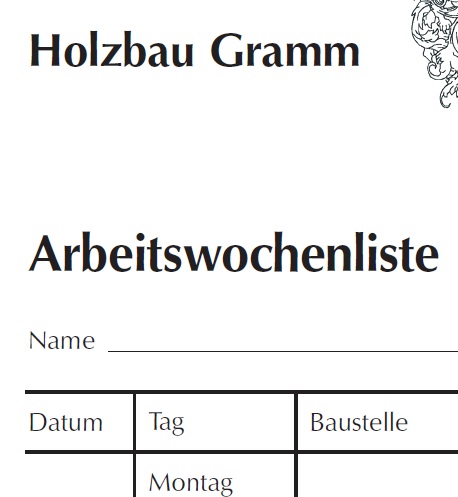
Font October SB roman und SB medium gesucht!
habe gerade einen Anruf aus meiner Hausdruckerei bekommen, dass deren Font October SB roman und SB medium 0 kb anzeigt und nicht mehr funktioniert. Ich konnte denen leider nicht aushelfen, wo man diese Schrift nachkaufen kann (oder downloaden falls freefont). Die Leute dort benutzen MAC. Weiß jemand von euch, wo man die herkriegt? Bekomme in den nächsten Minuten noch einen Screen. Angeblich soll sie recht unspektakulär wirken, ähnlich der Myriad.
Das war der Optima Clone der Firma Scangraphic.
SB bedeutet Scangraphic Bodytype (also für den Textbereich).
Es gab auch SH (Scangraphic Headline).
Diese Familie wie auch andere Clones der Firma Scangraphic werden nicht mehr geliefert.
dank deinem Tipp hab ich in meinen alten Scrangraphic Dr. Boeger GmbH Schriftenkatalog geschaut. Und siehe da, auf Seite 59 finde ich die October! Jetzt wundert mich aber gar nichts mehr, denn die Druckerei war einer der ersten Fotosatzstudios hier in der Gegend.
Mein Katalog hat den Index November 1985!